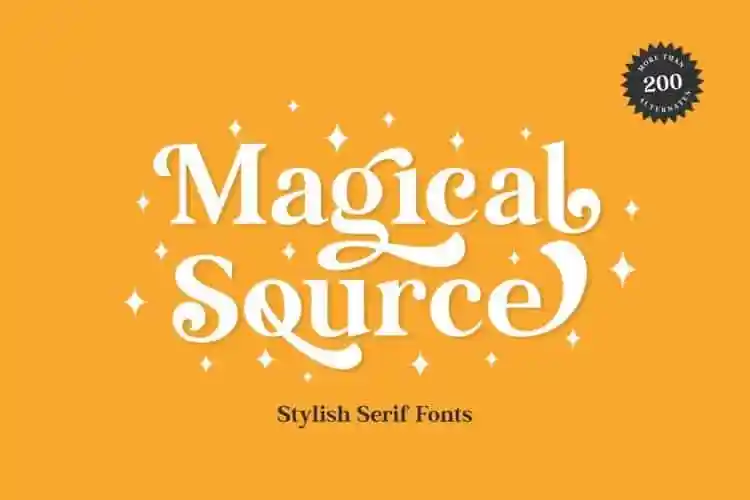
Magical Source Serif Font é uma elegante tipografia serifada que se destaca pela sua versatilidade e sofisticação. Este tipo de letra foi projetado pelo designer JavaPep através do site 99designs, apresentando um conjunto incrível de alternativas de caracteres tanto em letras maiúsculas quanto minúsculas para um toque a mais de originalidade. Esse estilo serifado é perfeito para aqueles que buscam uma fonte sofisticada e moderna. Além disso, esta fonte possui mais de 200 alternativas de caracteres, permitindo-lhe combinar estas opções criativamente segundo suas preferências pessoais. Mesmo sem ativar as alternativas, a Magical Source continua a oferecer um desempenho visual excelente, tornando-a uma escolha versátil para uma variedade de aplicativos. Seja para o headline, título, logotipo, marca, pull quote ou até mesmo os nomes personalizados, esta fonte proporcionará sempre um visual atraente e sofisticado.